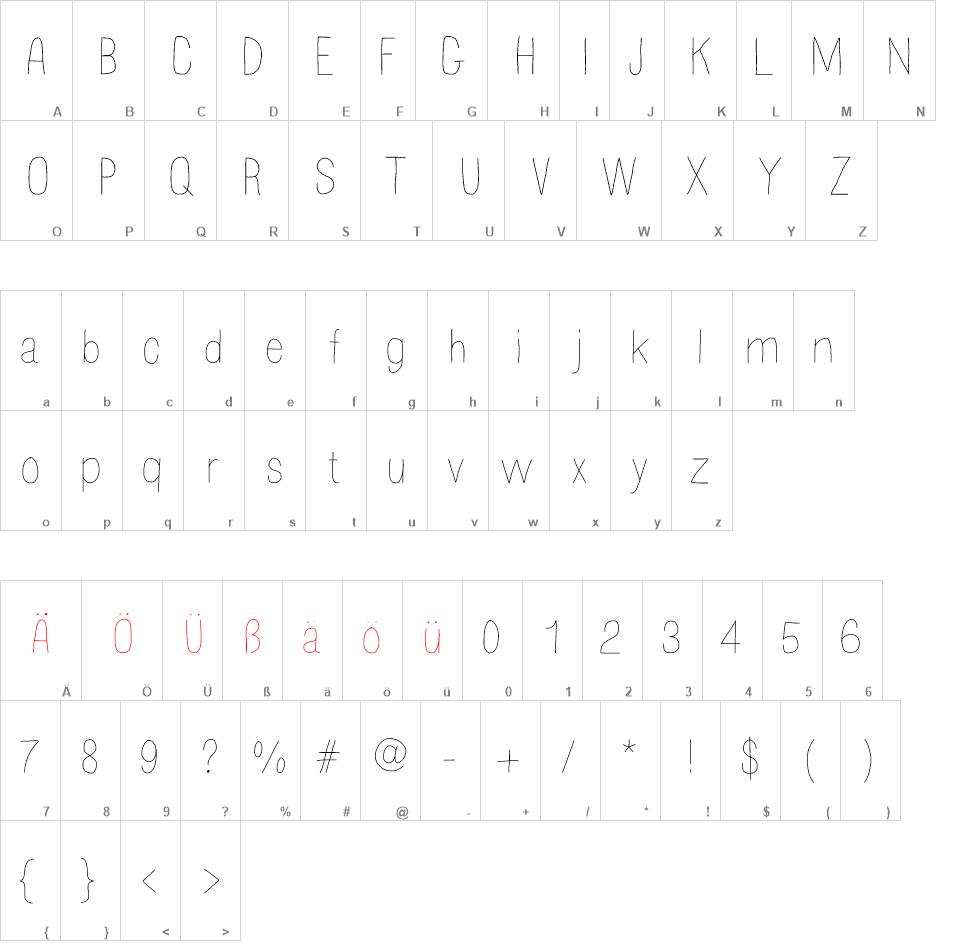
Mossy
Handschriftliche Schrift, basierend auf einigen Helvetica-Formen, so dünn wie Kate, wie Mossy, wie moosgewachsene Ideen über handgeschriebene Typografie.